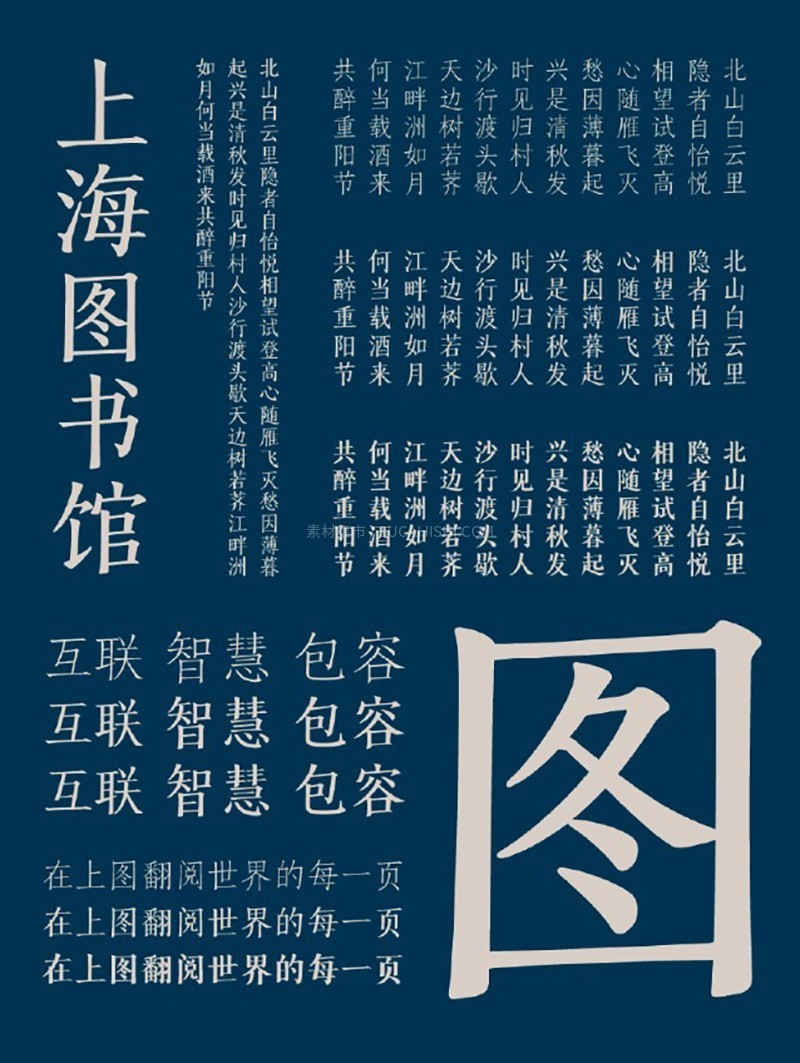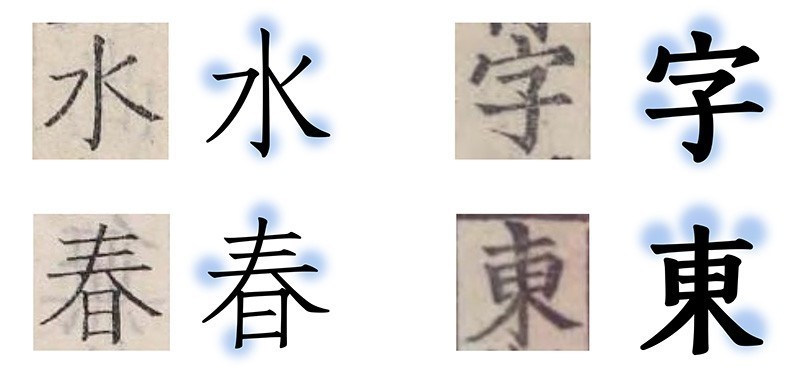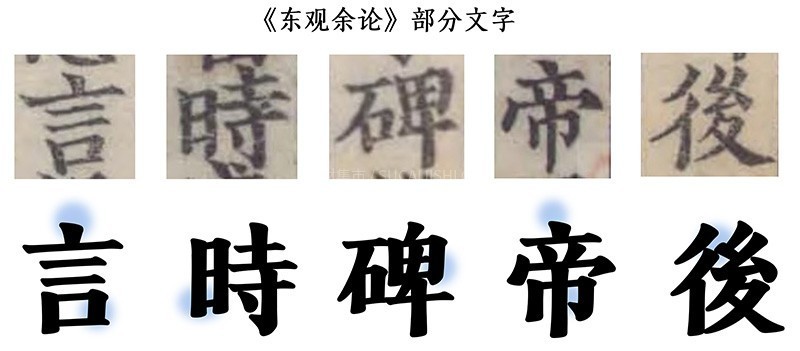
2023年4月,上海图书馆联合汉仪字库定制的专属字体“上图东观体”完成制作,经过内部测试后,现正式向社会发布。这套字体包含常规、细体和粗体三种规格字重,每种字重覆盖9169个字符,历时一年悉心打磨而成。富有书卷气和书写感的“上图东观体”,旨在为数字时代的阅读者和创作者保留见字如面、执笔抵心的文化传统与温度。